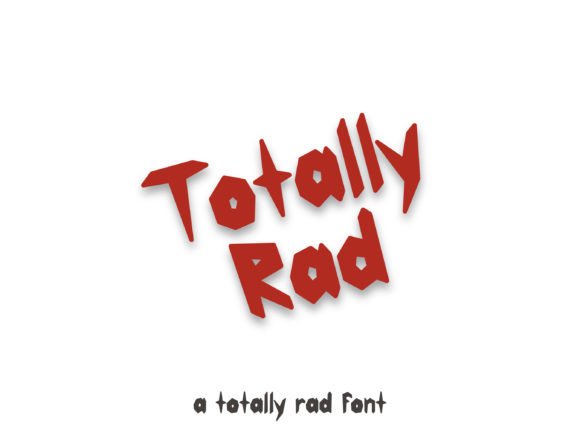
Totally Rad
適切なデザイン要素を見つけるのは難しい場合がありますが、Totally Radは作品を即座に引き立てる優れたコレクションを提供します。
POD(オンデマンド印刷)製品、結婚式の招待状、またはソーシャルメディアのグラフィックを作成している場合でも、Totally Radは理想的です。